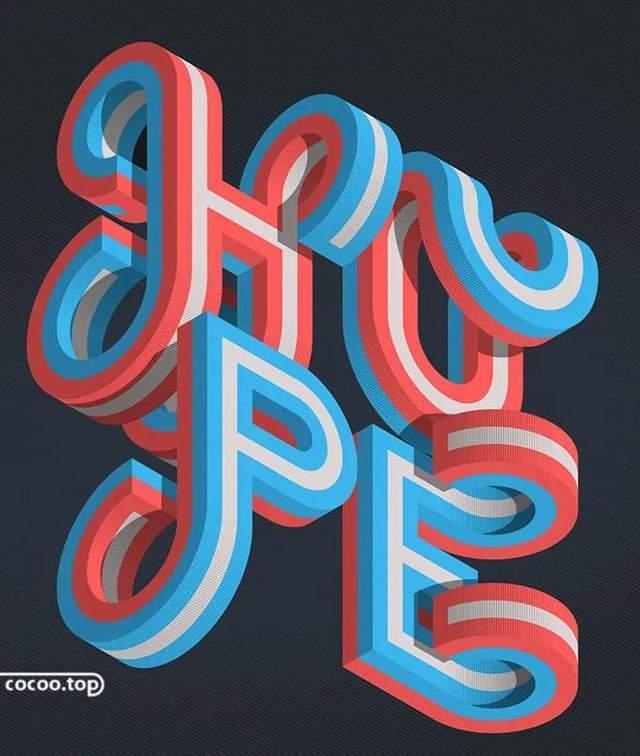
变形设计
在英文字体的设计过程中为使字体形态具有普遍性又具有强烈的个性,就需要对字体的结构进行处理。字体的变形一般要根据字形结构或一组词语的内容以及字数的多少、面积的大小决定,尽量不要过分的改变字体结构,不要过于夸大变形尺度。
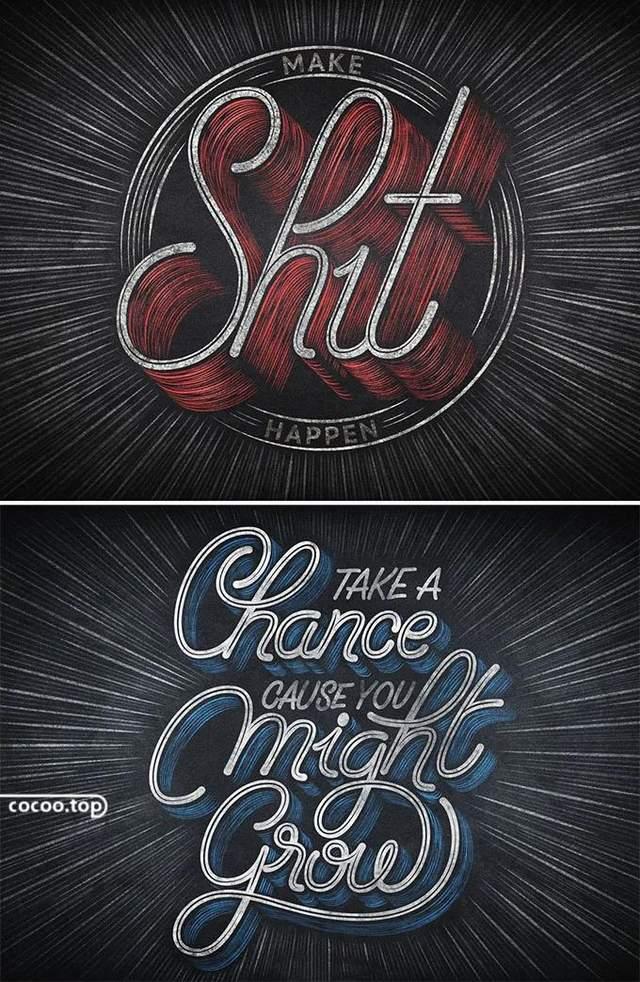
英文字体的变形手段、形式之多,可以说是五花八门,常见的几变形方式有压维变形、倾斜变形、弯曲变形、旋转变形、波浪变形、球状变形、环状变形、立体投影和透视变形等形式。
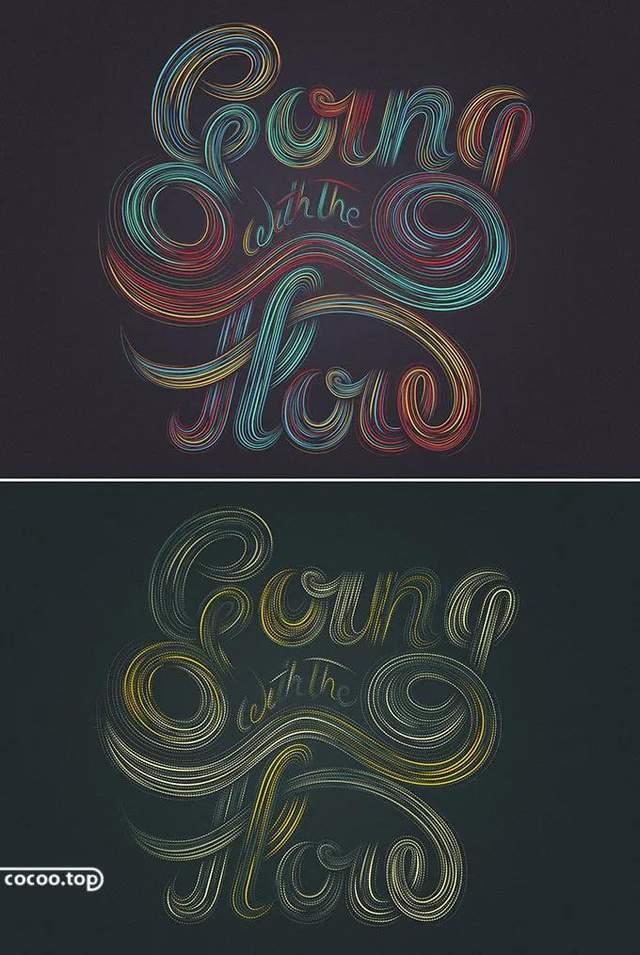
正负形设计
在英文字体设计时可以巧妙地利用正负形之间的虚实关系,增强作品的对比效果,使字体更具有活力,另外也可以采取正负形颠倒的手法即负形是图正形是背景,用正形去烘托负形形成视错觉,以增加画面的层次和立体感。
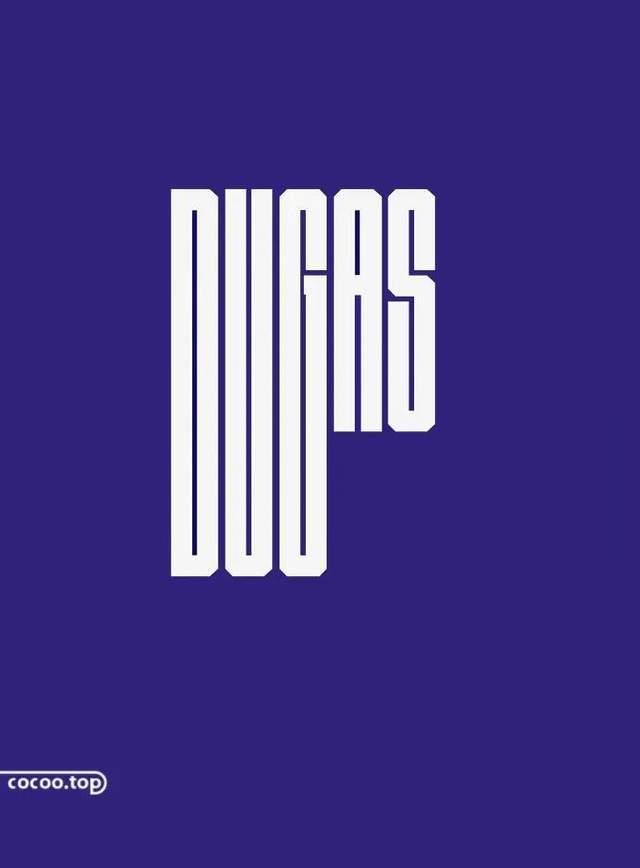
背景装饰设计
英文字体设计中的背景装饰是指在文字的背景上加上相应的装饰图形,以起到烘托和渲染效果,增加文字的表现层次和设计内涵,但应该注意的是不能画蛇添足,装饰风格应与文字的造型相统一。
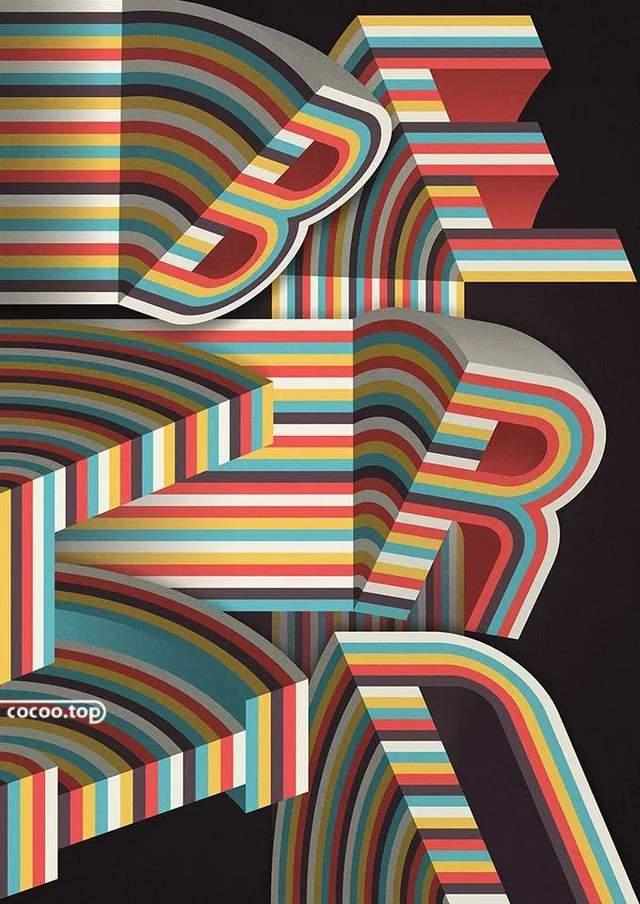
本体装饰设计
英文字体的本体装饰即对字体本身进行装饰,应注意的是所设计的装饰元素不能干扰字形结构,更不能影响文字的识别性,本体装饰中所添加的纹样、图案要与字体结构或字义相一致,不可生搬硬套。
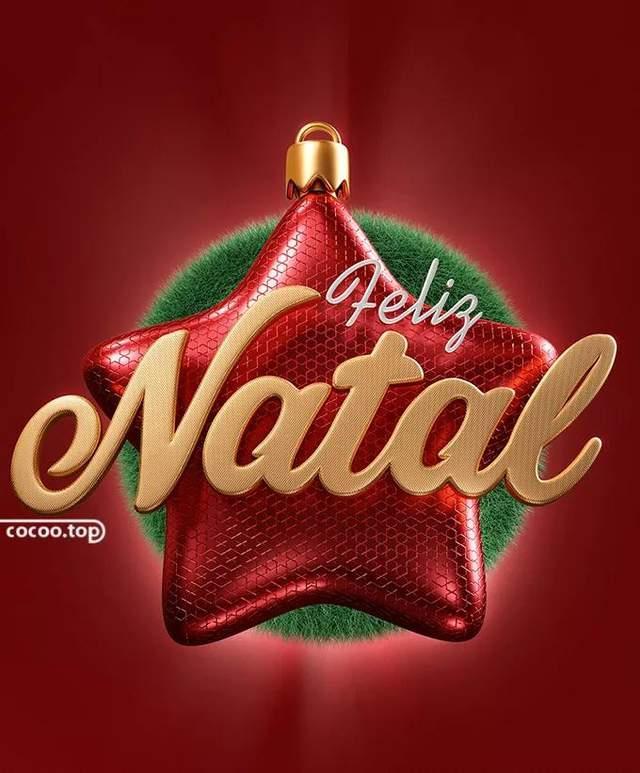
连接装饰设计
英文字体设计中时常采用一种连接装饰的字体设计,这种装饰型字体实际上是指在字与字之间可塑性较强的笔画,或笔画上进行装饰,通过这种装饰将字与字有机地连接使一组字变成一个整体。我们可以把一个字的笔画连接起来,也可以把相邻的字连接起来,使之呈现出或高或低或似外框的特征,从而产生秩序美感。
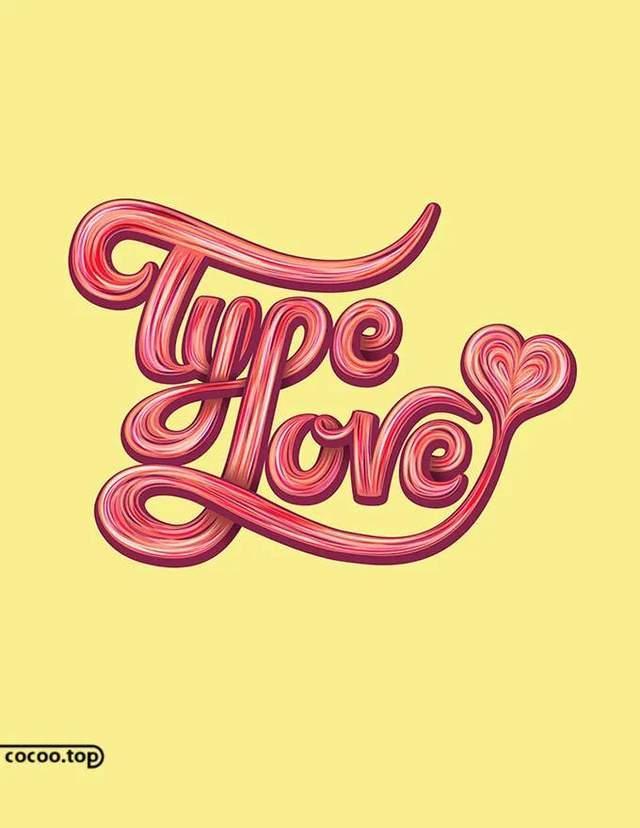
线条装饰设计
单线条或多线条对字体笔画进行装饰,它也是常用的字体装饰手法可以使字体形象更富。
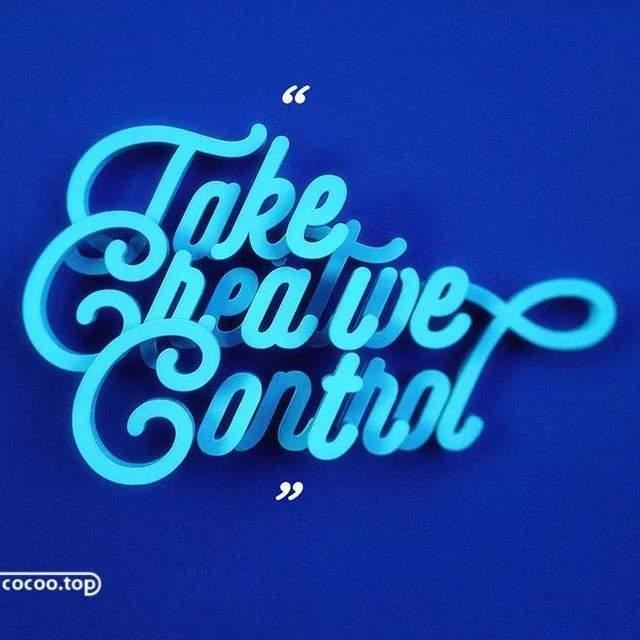
重叠装饰设计
重叠装饰设计主要有两种方法:一种是笔的重叠即将字的次要笔画叠加在主要笔画之上;另一种是字与字进行重叠双字或多字的重叠,重叠的目的是为了增强层次感。
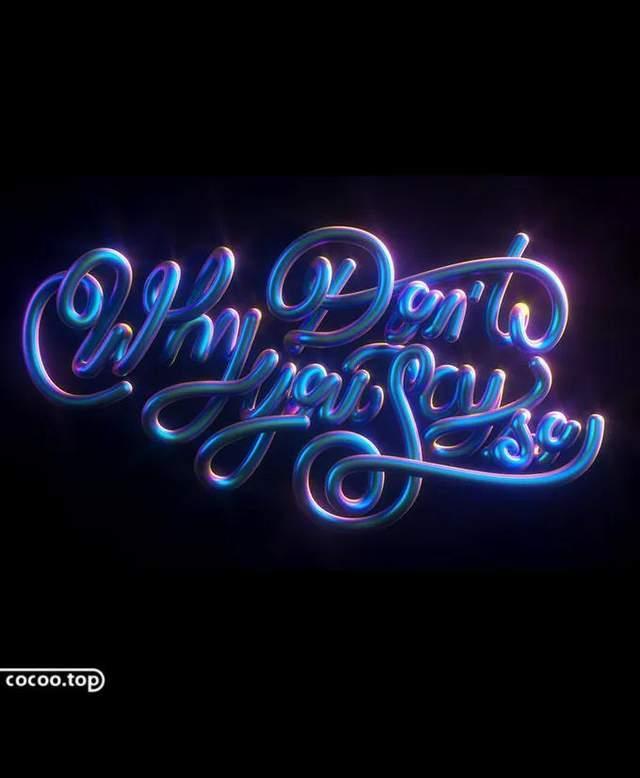
实心装饰设计
实心装饰设计是指只要字的外轮廓,而中间笔画全部省略,可以反白也可以涂黑,设计时一定要抓住字的外形特征。
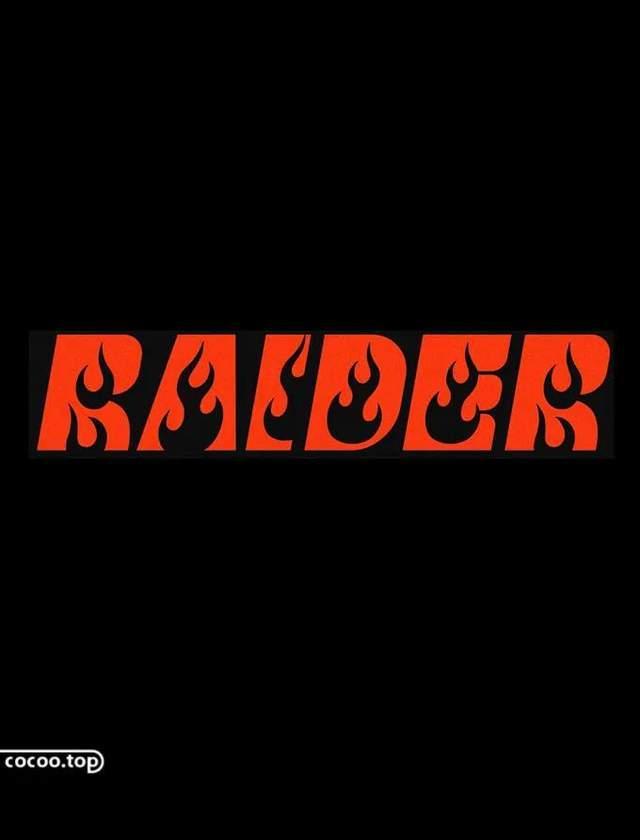
错位装饰设计
错位装饰设计就是将字体进行错位变化,使之产生律动和扩张的状态,同时增强了字体的视觉冲击力,这种字体在广告设计中常被运用。
综合装饰设计
将几种字体装饰形式相互结合设计,例如:在本体装饰的基础上进行立体效果装饰,可以增强和丰富画面的设计效果。
字体的形象设计
根据字体内容从装饰美化的角度出发,发将文字与各类图形相结合。这种设计特点是把握特定文字个性化的意象将文字的内涵通过视觉化的形象传达出来,从而增强趣味性。
其基本设计手法有两种:一种是通过添加形象形成半文半图的效果;另一种是不与具象图形结合而是单纯以笔画的多少、大小与空间结构的配合,进行灵活抽象的表达。
字义设计
字义设计是指在设计中用字体本身的含义,用形象化的方法表述出所要传达的主题含义,与字体形象设计不同的是它塑造的形象通常是表现字体的本义。
立体表现设计
立体表现设计是把平面的字体设计成具有立体感,更具有视觉冲击力的字体形态。常用的表现方法有透视法、浮雕法、阴影等。
肌理表现设计
肌理是指物体表面的纹理不同的肌理变化,带给我们不同的视觉和心理感受,在进行字体设计时我们可以采用不同的工具制造不同的肌理,也可以用不同的材质表现不同的肌理。
色彩表现设计
在设计中如何决定一幅设计作品的色彩,首先要虑到我们所针对的目标群体,因为针对不同的目标群体,在英文字体设计亦是如此。
例如:针对妇女、儿童用品的字体设计采用对比柔和的色调,给人温暖柔和的感觉;针对男性用品的字体设采用黑色、银灰色、体现现代感、阳刚之气。只有了解色彩的性格和它带给我们的视觉感受,才能更好地运用它。
手写字体
手写字体在日常生活中随处可见,以各种方式传递着信息,手写字体设计是将字体进行个性化的演绎,这样设计出的字体不同于印刷字体,它有着鲜明的个性特征,能给人以自由奔放的感觉,并具有不可模仿的随意性和独特的视觉效果。